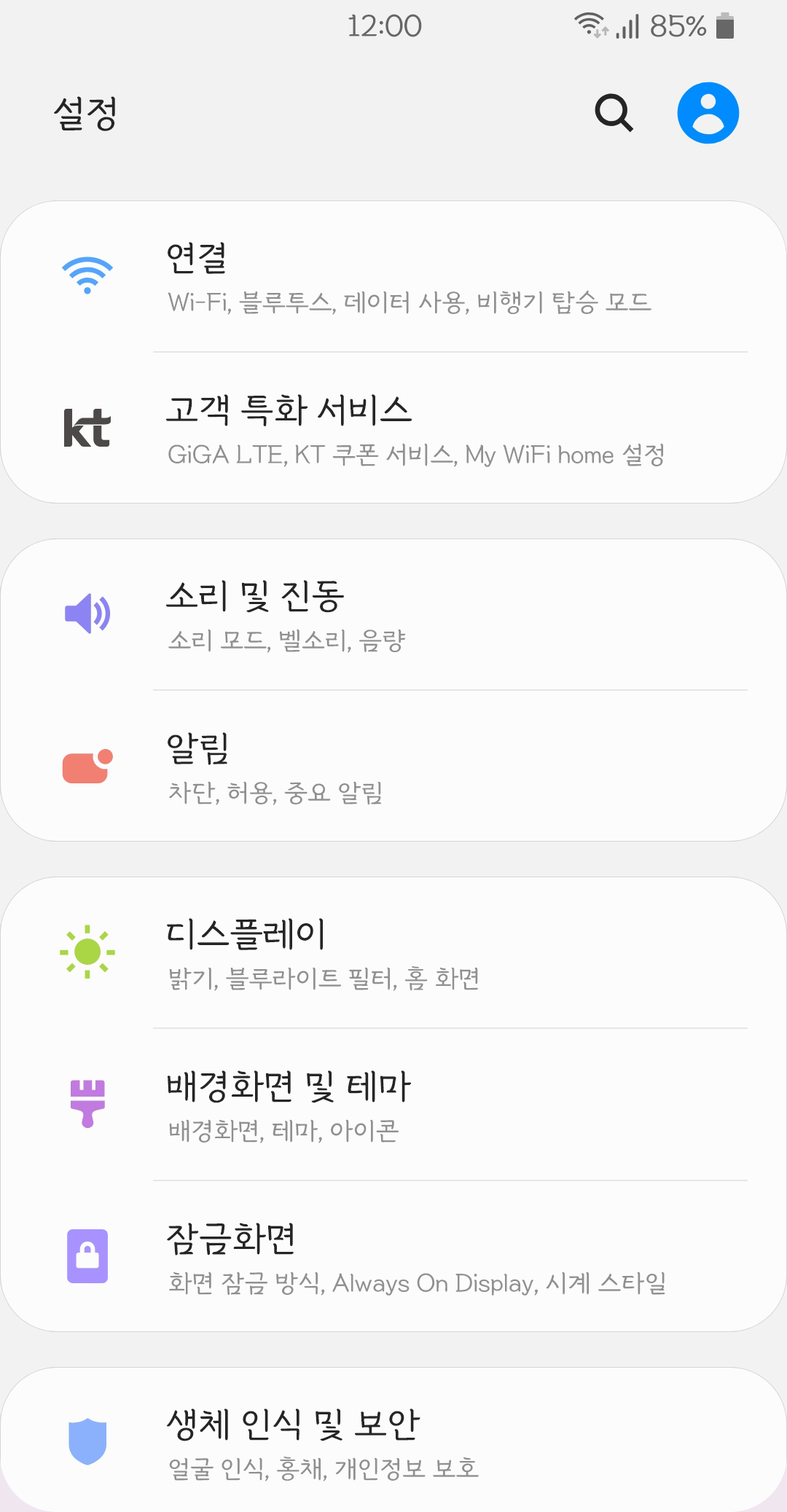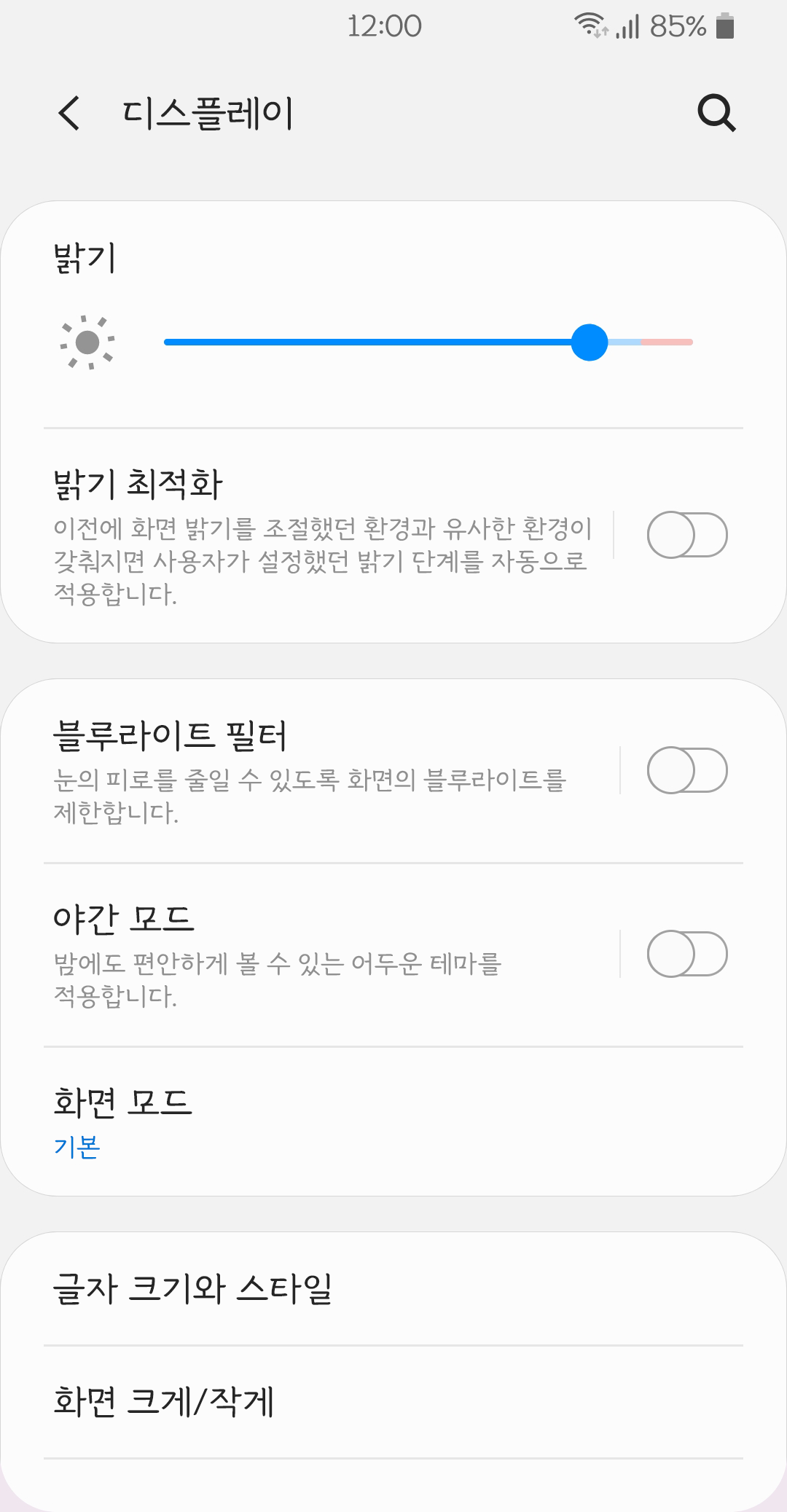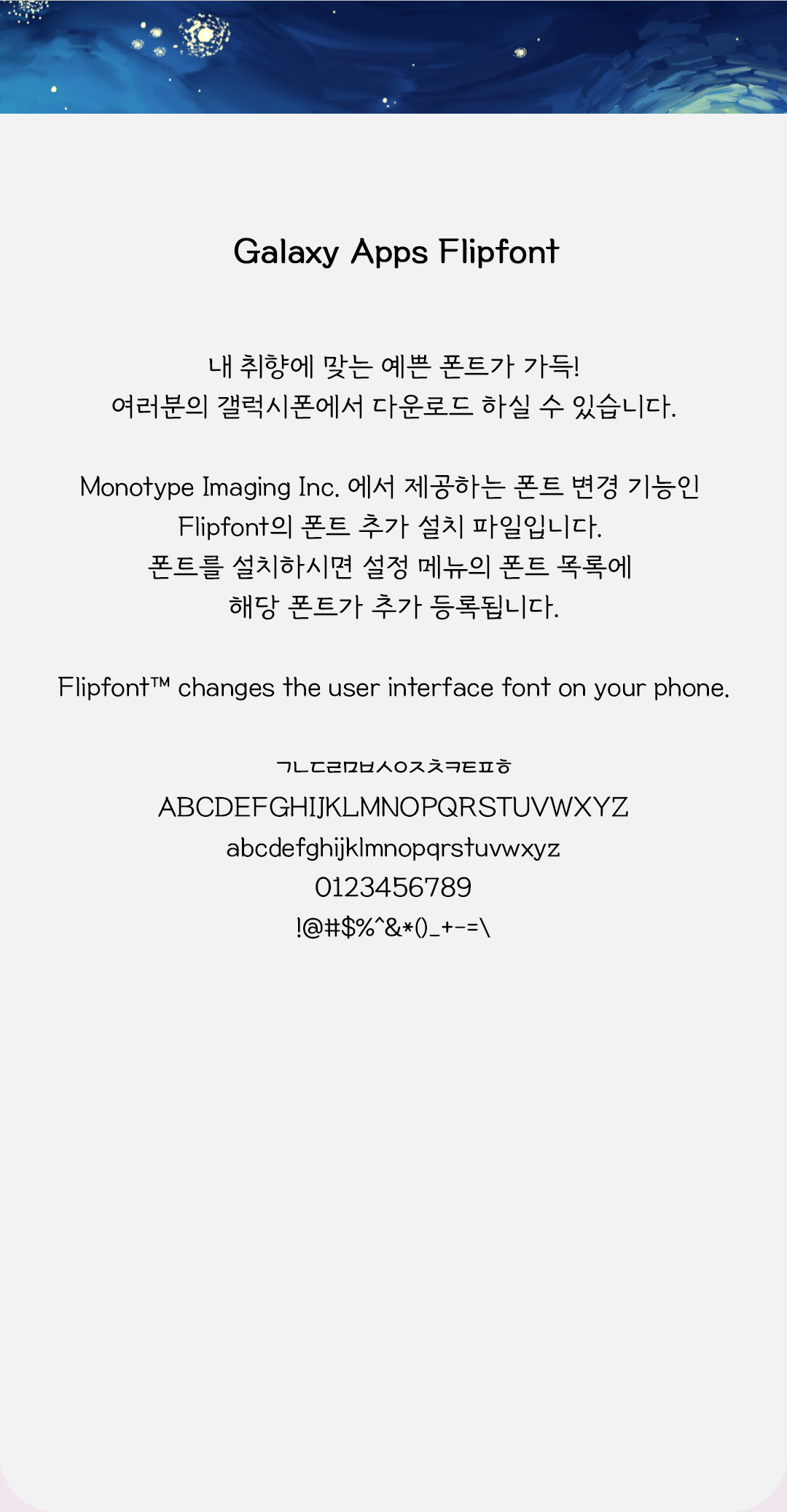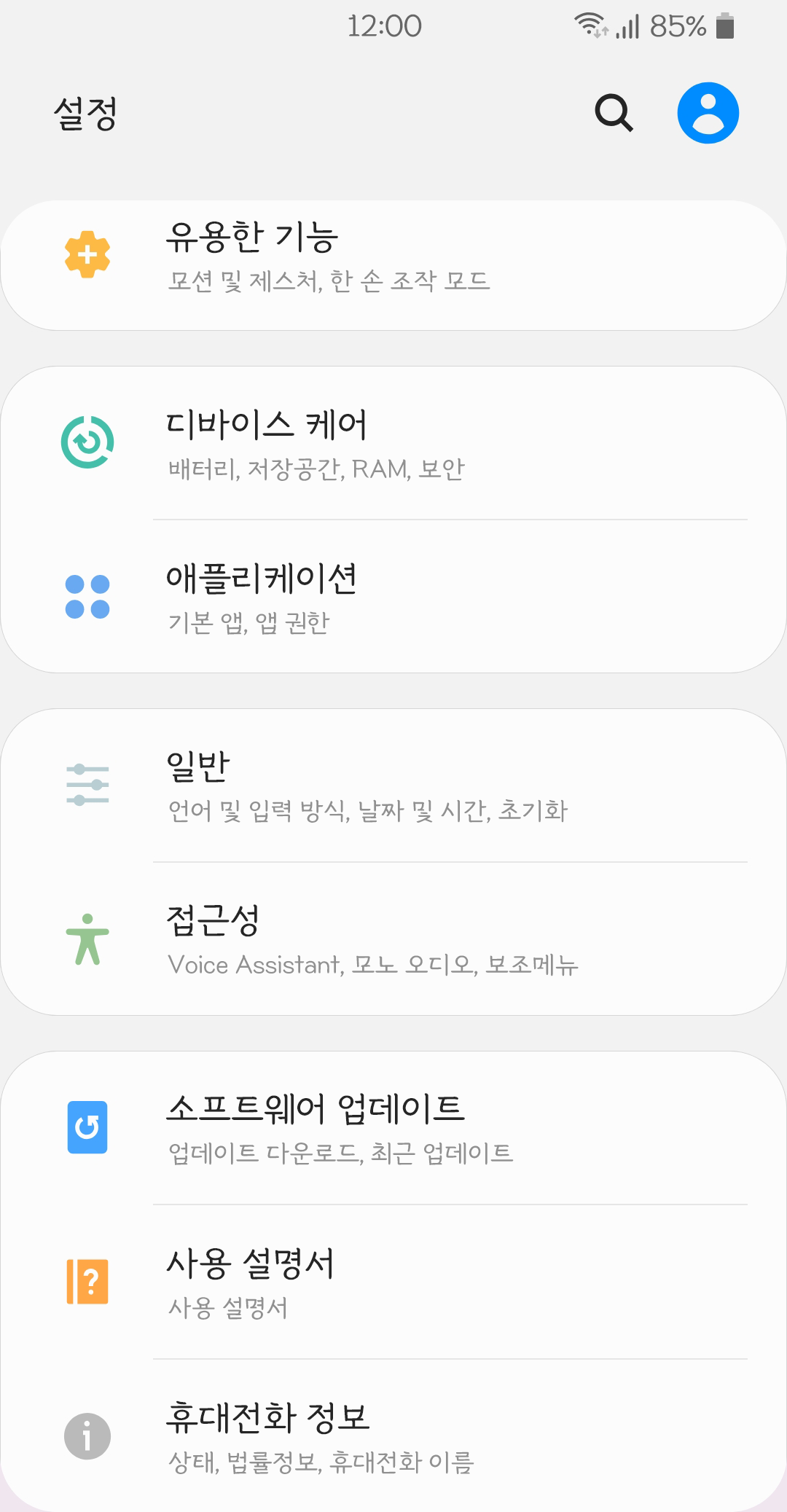
부드럽고 시원시원한 손글씨 느낌의 서체입니다.
펜으로 차분하게 눌러써, 중성 획의 끝에 잉크가 뭉친 모양의 세리프가 특징입니다.
서체의 얼굴인 'ㅇ','ㅎ'의 원형을 기울이고 'ㅁ'의 획을 흘려쓴 형태로 디자인하여 서체에 손글씨같은 특성을 부여하였습니다.
부드럽고 시원시원한 손글씨 느낌의 서체입니다.
펜으로 차분하게 눌러써, 중성 획의 끝에 잉크가 뭉친 모양의 세리프가 특징입니다.
서체의 얼굴인 'ㅇ','ㅎ'의 원형을 기울이고 'ㅁ'의 획을 흘려쓴 형태로 디자인하여 서체에 손글씨같은 특성을 부여하였습니다.